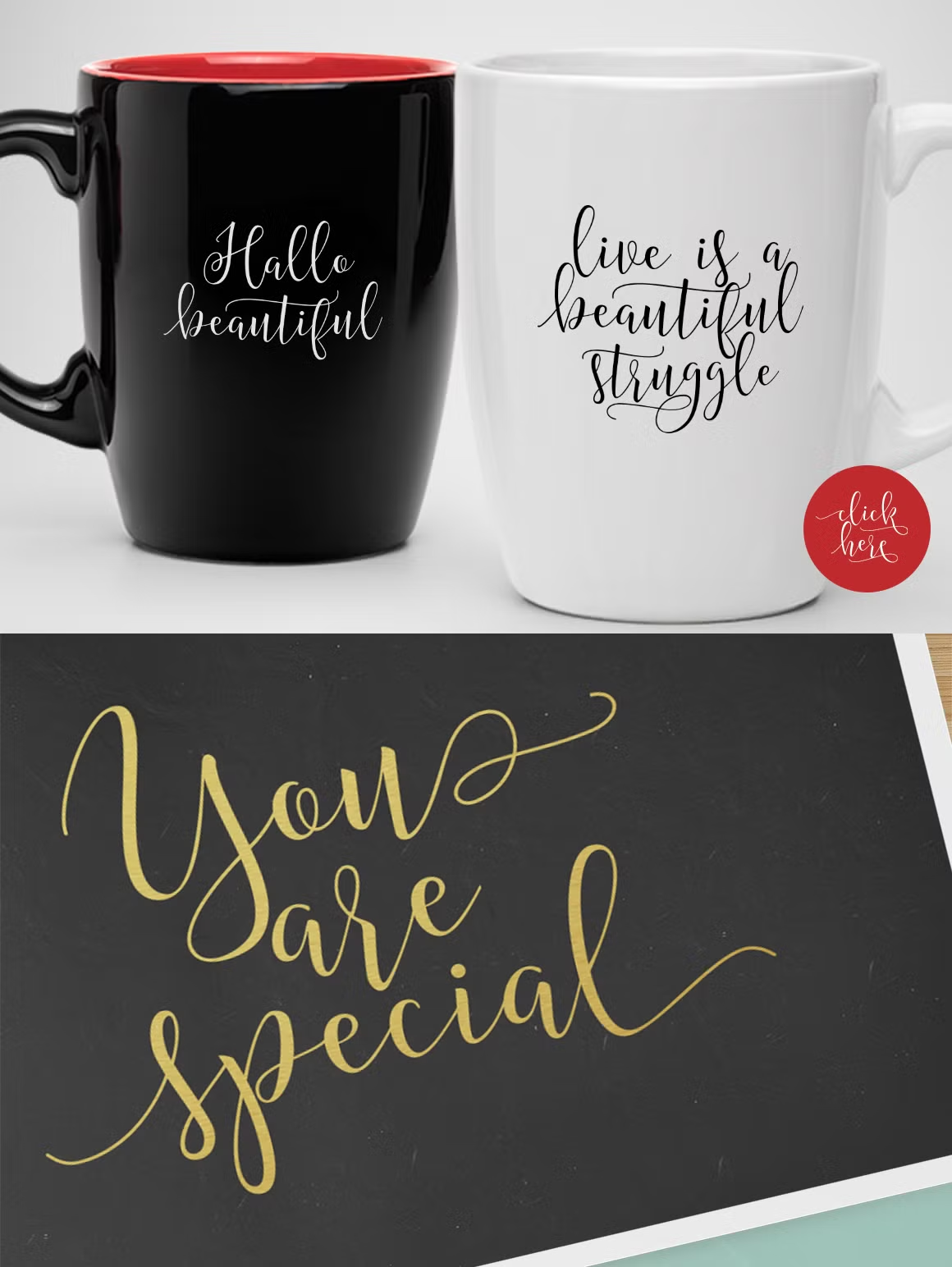
Amberlight Font
Présentation Amberlight Script : un nouveau script frais et moderne avec un style de calligraphie doux, des personnages décoratifs et une ligne de base dansante ! C’est tellement beau sur les invitations, les supports de marque, les cartes de visite, les citations, les affiches et bien plus encore !
Amberlight est livré avec 335 et 120 nouveaux ensembles stylistiques et personnages Swash. Les caractères alternatifs ont été divisés en plusieurs fonctionnalités OpenType, telles que les ensembles stylistiques, les alternatives contextuelles et la ligature. Ces fonctionnalités sont accessibles à l’aide de programmes compatibles OpenType tels qu’Adobe Illustrator et Adobe InDesign.